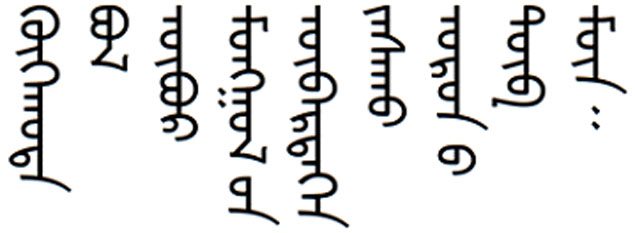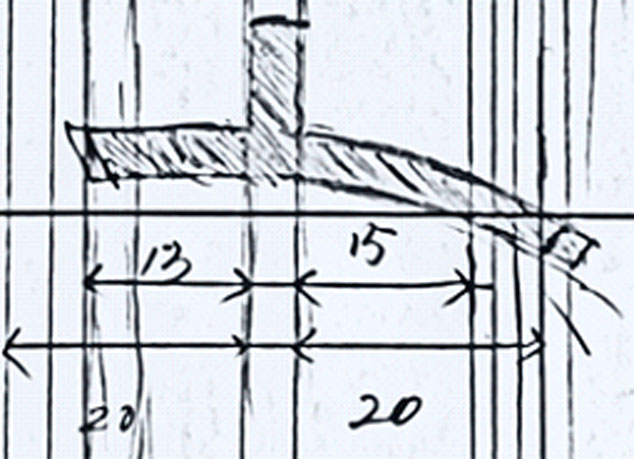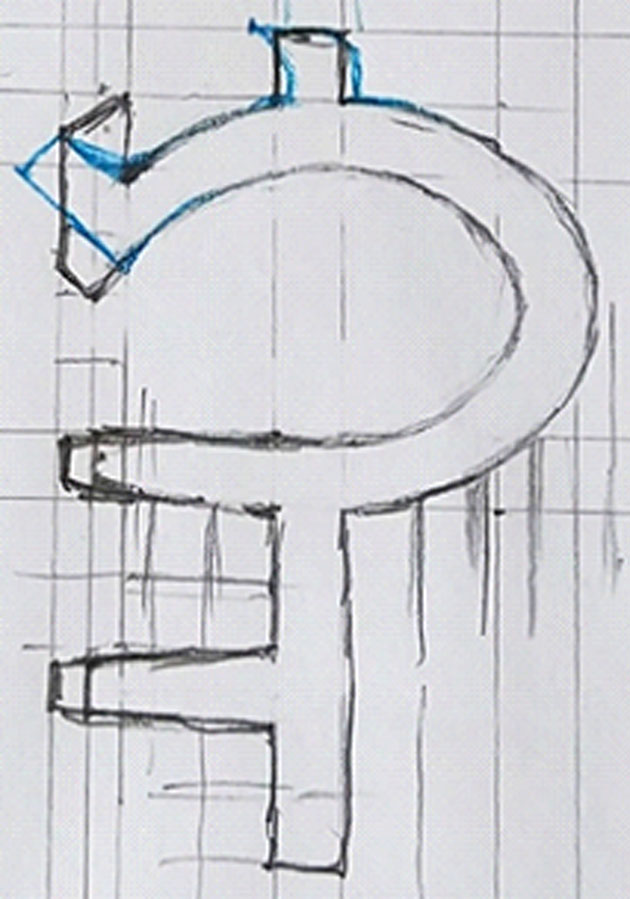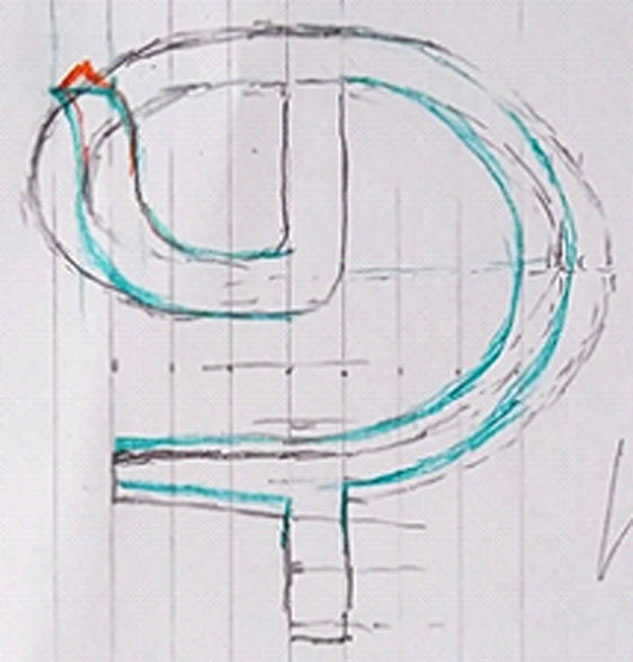
蒙古文无衬线报体字形集
一、创作目的 当今是网络化时代,智能手机、平板电脑等电子产品已经成为人们生活、学习、工作不可或缺的必品。但是,现有蒙古文字体都不太适应这一“时代需求”,已成为制约蒙古文在电子产品中广泛应用的重要因素之一。
为了探索、发展和丰富蒙古文字体及其设计方法,在培养和提高蒙古文字体设计能力的同时,面向机、平板等电子产品(屏幕)的应用需求,基于“蒙古文报体”的笔画及其结构特点,借用现代拉丁文、阿拉伯文无衬线字体的笔形和笔法(特点)设计了本作品。
二、创作过程 设计之初,从丰富的传统蒙古文图书文献中寻找并学习风格特殊的字体(形),感受这些风格特殊传统蒙古文字体(形)的创作目的和呈现的效果,从中寻找创作灵感。
例如:传统蒙古文杂志《影剧》1990年3期中一幅摄影作品的说明文字的“笔形”极具冲击力(图2.1),有别于现代蒙古文字体;传统蒙古文图书《蒙古族文献优秀遗产》的标题文本的风格突出(图2.2),其中部分蒙古文“笔画”极其紧凑、识读性很强,这是我们寻求已久的特点。对此,我们基于传统蒙古文文献经典《甘珠尔》(清内府刻本,1720年,图2.3)和上世纪初的经典蒙古文字体(图2.4)进行了对比分析,总结后获得了基本设计思路和字形结构雏形。
图2.1:杂志《影剧》1990年3期
图2.2:图书《蒙古族文献优秀遗产》
图2.3:文献《甘珠尔》清内府刻本,1720年
图2.4:上世纪初经典蒙古文字体
蒙古文报体”是蒙古文现代出版中常见字体之一。蒙古文报体的风格特点突出,其笔画舒展、线条流畅、笔画结构简单且紧凑,同时其笔画结构也已非常稳定。研究发现,蒙古文报体在小字号可读性方面有“先天”优势。
以“蒙古文报体”的笔画及其结构为基础,借鉴电子产品中应用广泛的拉丁文、阿拉伯文无衬线字体的笔形、笔法(特点),本作品用专业矢量图形设计软件完成了图(字)形集,其中包含48个独立图(字)形(请看“附件:图(字)形集”)。
目前,本作品已涵盖传统蒙古文的基础字形。初步产品化试验(图2.5)证明,本作品已具备基于国家标准《信息技术 传统蒙古文名义字符、变形显现字符和控制字符使用规则(GB 25914-2010)》开发现代蒙古文计算机字库的初始条件。
图2.5:初步产品化试验
当然,本作品存在诸多的成熟或不满意的地方,例如:几组大曲线的半径(图2.6)、折线角度等。部分图(字)形还需要通过实际应用中进行检验和优化修订,例如:传统蒙古文辅音字母HA(阳性)词首(图2.7)笔画设计、传统蒙古文辅音字母BA和PA字形(图2.8)的对比比例等。
图2.6:大曲线的半径和折线角度(手稿)
图2.7:传统蒙古文辅音字母HA(阳性)词首笔画
图2.8:传统蒙古文辅音字母BA和PA字形的对比
本作品不仅继承了蒙古文报体的笔画舒展、线条流畅、笔画结构简单且紧凑等特点,还因借鉴了拉文、阿拉伯文无衬线字体的笔形、笔法特点,从而获得了单位面积信息量大、小屏幕小字号显示清晰、适应多终端等特点,产品化试验上获得了全新的体验。
本作品的设计创作始于2017年03月,经过近一年半的努力,于2018年07月基本完成基础矢量图(字)形集的设计。
三、独创性声明 该作品由内蒙古社会科学院蒙古语信息技术研发(MIT)中心的呼斯勒独立创作完成,且不存在抄袭、复制他人作品的情形。